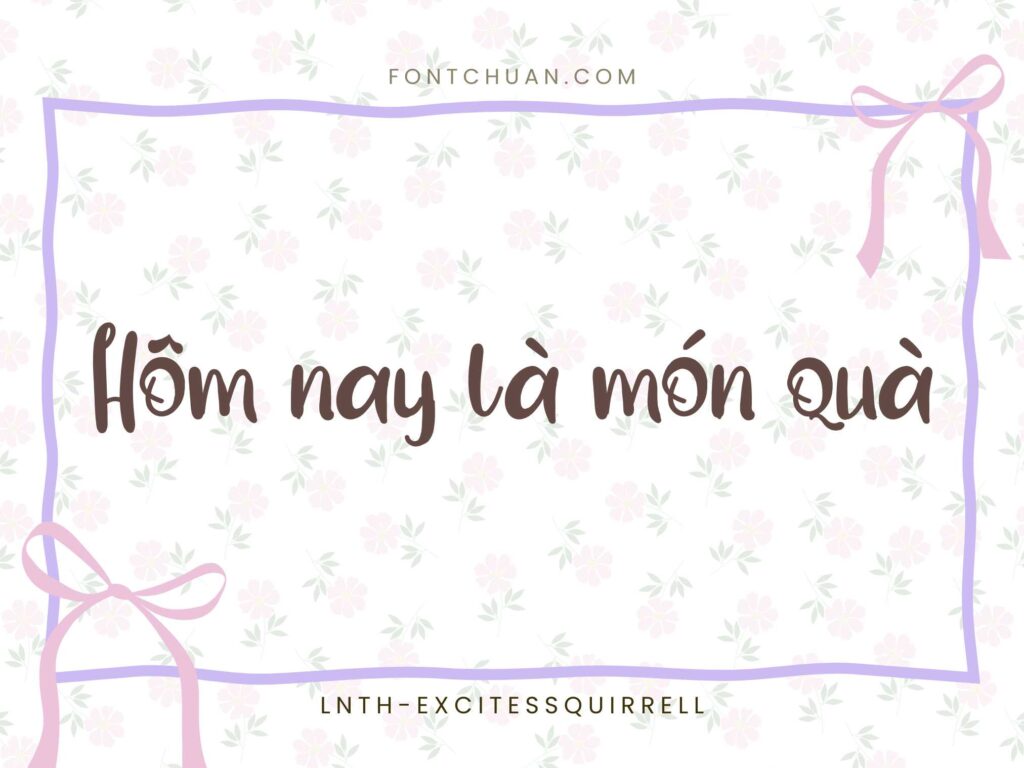
Font LNTH Excites Squirrell Việt Hóa
Excites Squirrell là một phông chữ viết tay độc đáo, mang phong cách vui tươi và sáng tạo. Với các đường nét mềm mại và ngẫu hứng, phông chữ này tạo cảm giác thân thiện và gần gũi, phù hợp cho nhiều dự án thiết kế cần sự phá cách và nghệ thuật. Nhờ được Việt hóa bởi LNTH, Excites Squirrell hỗ trợ đầy đủ các ký tự tiếng Việt, giúp người dùng dễ dàng áp dụng trong các dự án đa ngôn ngữ. Phông chữ này đã được sưu tầm và đăng tải bởi thành viên của Font Chuẩn nhằm đáp ứng nhu cầu đa dạng của cộng đồng thiết kế.
Về đặc điểm thiết kế, Excites Squirrell sở hữu các ký tự được vẽ tỉ mỉ với những đường nét tự nhiên và phóng khoáng, mang lại cảm giác sống động và tràn đầy năng lượng. Phông chữ này đặc biệt phù hợp cho các dự án như thiệp mời, bìa sách, poster, logo và các ấn phẩm quảng cáo, giúp truyền tải sự sáng tạo và độc đáo. Ngoài ra, Excites Squirrell cũng thích hợp cho các sự kiện như lễ hội, sinh nhật, Halloween và Trung thu, mang lại không khí vui tươi và sôi động. Trong lĩnh vực ngành nghề, phông chữ này được ứng dụng rộng rãi trong quảng cáo, thiết kế thiệp cưới, giáo dục và công nghệ, góp phần tạo điểm nhấn ấn tượng và chuyên nghiệp cho các sản phẩm và thương hiệu.